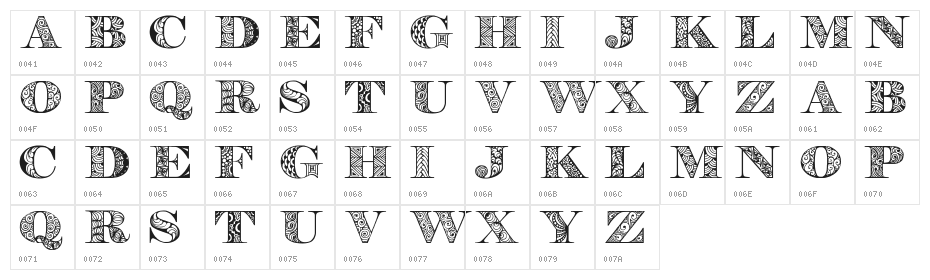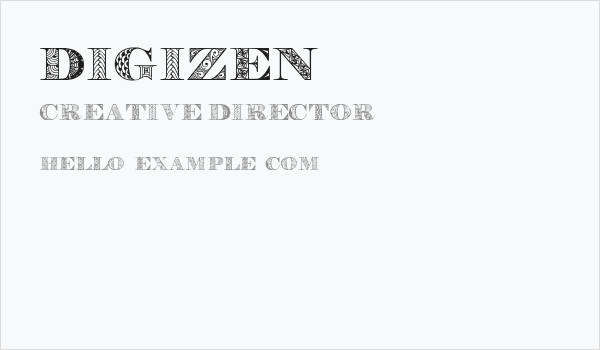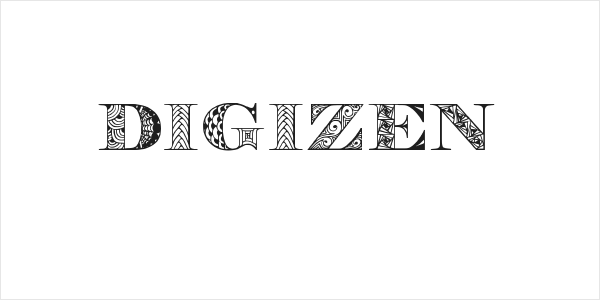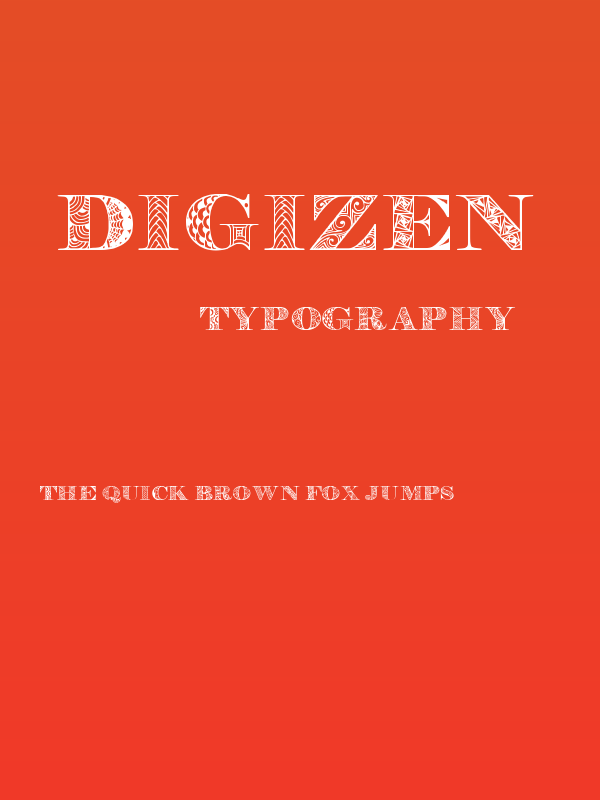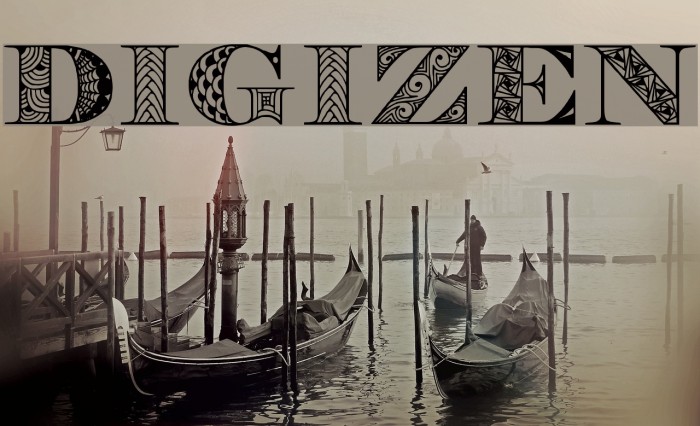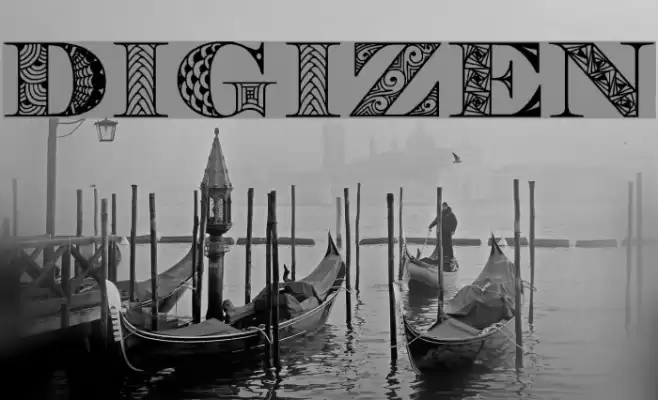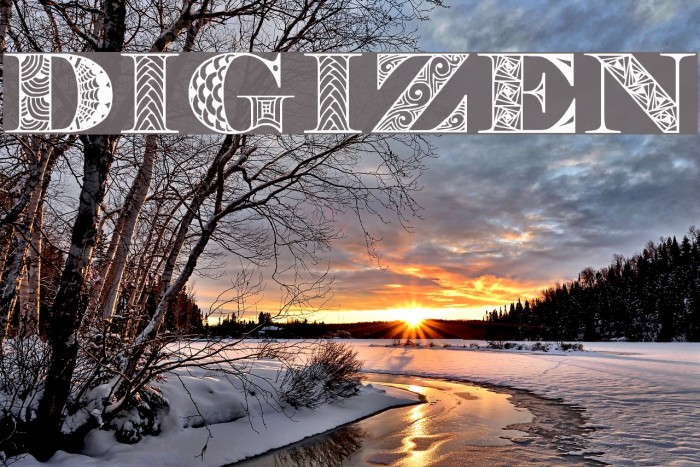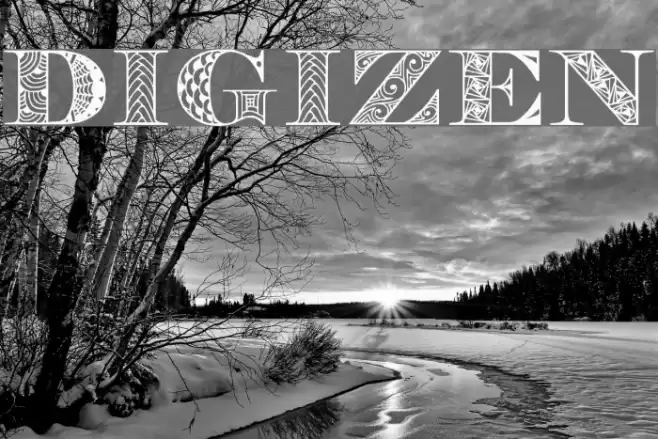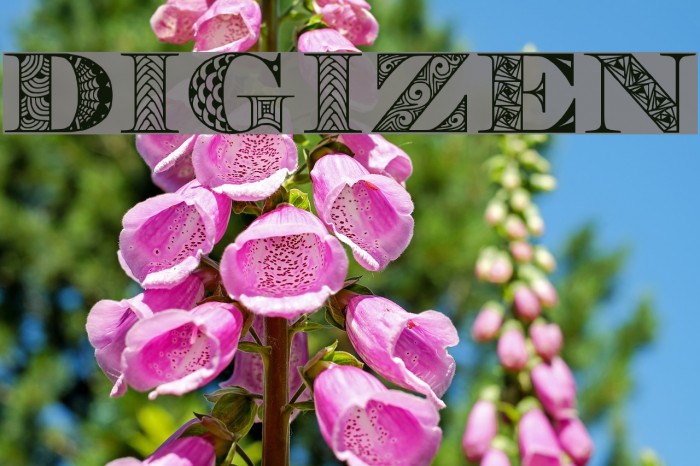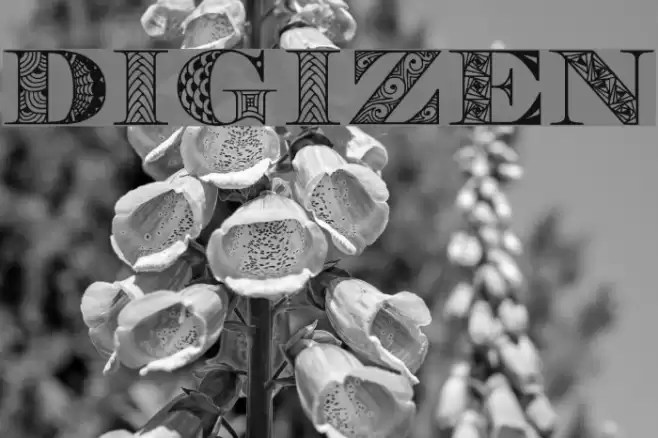
Digizen Font
✎ Serif
| Категория | Serif |
| Область применения | Logos, Headlines, Artistic projects |
| Рекомендуемые проекты | Ideal for wedding invitations, artistic posters, branding for luxury products, and decorative book covers. |